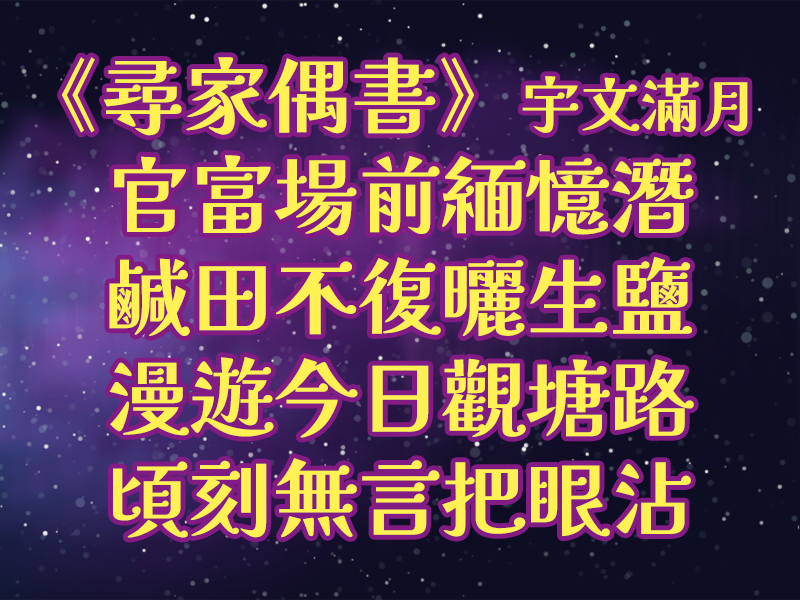
宇文天穹
「宇文天穹(UoqMunThenKhung)」爲適用於繁體中文環境的開源字型,它以日本「解星計劃」開發的「解星」字型爲基礎,參照傳承字形標準化文件的推薦形體修改爲中文傳統字形,補製欠缺的漢字。
製作說明
漢字字形向來千姿百面,印刷或屏顯的設計美觀需求與手寫書法的審美角度不盡相同,符合字理字源的傳統正字與書寫便捷的俗體變體也各有着眼點。而會使用傳統中文、繁體中文的地區,也有不同的敎育和非敎育標準或參考,這些標準或參考各有其立場,各有不同的適用與不適用場合,有時或會令有人顧此失彼之感。
考慮到此字型畢竟爲印刷或屏顯設計,儘管糅合了一些書寫特色,但仍以明黑等印刷字體爲主軸,滿月製作繁體中文版本時,主要參考傳統印刷字形,即「傳承字形」(或稱「舊字形」),並以開源組織「一點字坊」維護的傳承字形標準化文件爲依據。其推薦形體平衡了字理字源、設計審美與約定俗成三者之考慮,不會爲了其中一者就無視其他方面的需求,堪稱完備。推薦形體也跟各地看到的傳統印刷字形相當一致,放諸四海皆合宜,方便跨地區應用。
唯因本字形也非完全與明體、黑體一致,因應其設計所需及綜合考慮,它有個別地方跟傳承字形標準化文件上的推薦形體有異。包括:
因末端小圓形的設計,「豎曲」會跟「豎曲鈎」混同,「橫曲」會跟「橫曲鈎」混同,「捺」會跟「捺鈎」混同,「扁捺」會跟「扁捺鈎」混同。
「豎」與「挑」會合成「豎挑」一筆。
撇筆、捺筆起筆處相觸或會使字形太黑,因此未必相觸。這會導致「木部件」與「朩(小木)部件」混同,故後者盡量改用有鈎的造型。
「肖部件」、「害/憲/㓞/丯部件」、「茲部件」、「匀部件」、「曷部件」、「夜部件」採用第二式。
「雨部件(在上)」的四點向內聚。
若不構成部件對立,框內橫筆末端是否與外框相觸,皆維持原「解星」字型之設計。